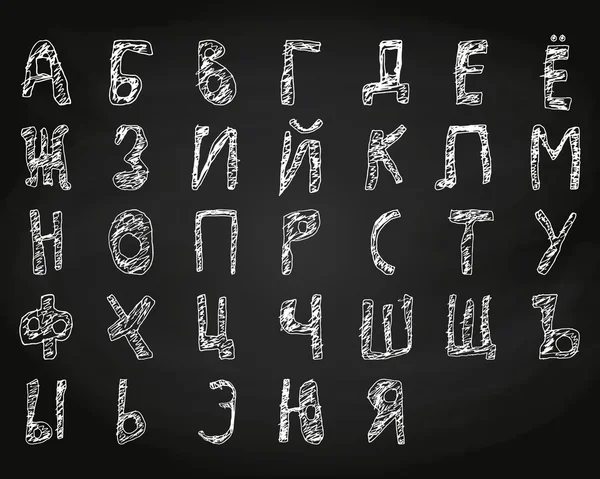
Оформление меловых досок в кафе, баре и ресторане
Еще в конце XIX века рестораны стремились превратить меню в настоящее произведение искусства. Сейчас мир возвращается к практике эстетики в обыденных вещах, но вместо витиевато оформленных фолиантов о предложениях кафе или ресторана гостям сообщают меловые доски. Их использование позволяет превратить меню над барной стойкой в оригинальное интерьерное решение.
Часто меловые доски устанавливаются при входе в кафе для привлечения клиентов. Их оформление или меловой леттеринг — увлекательная техника, которая позволяет создавать шедевры, используя кусочек мела. Масштабное увлечение леттерингом началось 10 лет назад. Идея пришла к нам из европейских стран и блестяще вписалась в винтажный ажиотаж и повальное увлечение хэндмейдом.
Кстати, меловой леттеринг — это не только модно: оформление такими досками кафе, бара и ресторана выгодно и удобно.
Что писать на меловых досках?
Интерьер заведения стал одной из главных характеристик, по которому горожане выбирают места для дружеских или романтических встреч. Владельцы ресторанов, уловив эту тенденцию, все чаще зовут специалистов для оформления меловых досок, чтобы меню над баром идеально вписывалось в интерьер.
Кроме меню, мелками выполняют оригинальные надписи, пишут шутки, загадки и просто дурачатся. Если остроумных идей не возникает, на помощь приходит Интернет, где можно найти огромное количество различных цитат на тему выпивки, любви, еды и жизни.
Профессионалы советуют выбирать краткие фразы в 4-5 слов, чтобы оставить на меловой доске место для различных ленточек, маленьких иллюстраций или флоришей. Слишком много слов загромождают доску, не оставляя места для других элементов. А они важны: ведь очаровательный флориш над буквой Й или свош из буквы Е и делают изображение оригинальным и запоминающимся.
Как писать?
Меловая доска в кафе, баре и ресторане должна выполнять свою задачу, то есть информировать посетителя о позициях меню и подчеркивать особенности интерьера. Если мы говорим об уличном штендере, то надпись на нем должна быстро читаться. Есть несколько общих правил, которых стоит придерживаться при оформлении меловой доски:
Помните о контрасте. Тонкие белые буквы почти незаметны на темном фоне, поэтому, работая с мелом, выбирайте жирный шрифт.
Учитывайте особенности композиции. Меловые доски в ресторанах и кафе могут быть расположены довольно высоко. Если гости видят ее снизу, пропорции искажаются.
Принимайте во внимание формат ресторана. Оформление меловых досок должно сочетаться с общей атмосферой, так, изысканный готический шрифт будет хорошо смотреться, если в интерьере есть поддерживающие его детали.
Зачем писать?
Оформление кафе и ресторанов с помощью меловых досок помогает нам отойти от эры масс-маркета в сторону чего-то индивидуального, выполненного с душой. В США пользуется популярностью сеть магазинов, где все ценники для товаров пишут обычным маркером. В каждой точке работает свой оформитель, который пишет цены от руки в одном стиле. Меловой леттеринг работает также: он дает возможность за весьма умеренную цену позиционировать себя как заведение с индивидуальным подходом.
KG Broken Vessels — это набросанный вручную шрифт для классной доски без засечек. Он пышный и смелый, что делает его идеальным для использования в дизайне, ориентированном на детей. Шрифт имеет игривую эстетику, поэтому он отлично подойдет для приглашений на день рождения или футболок для детей.